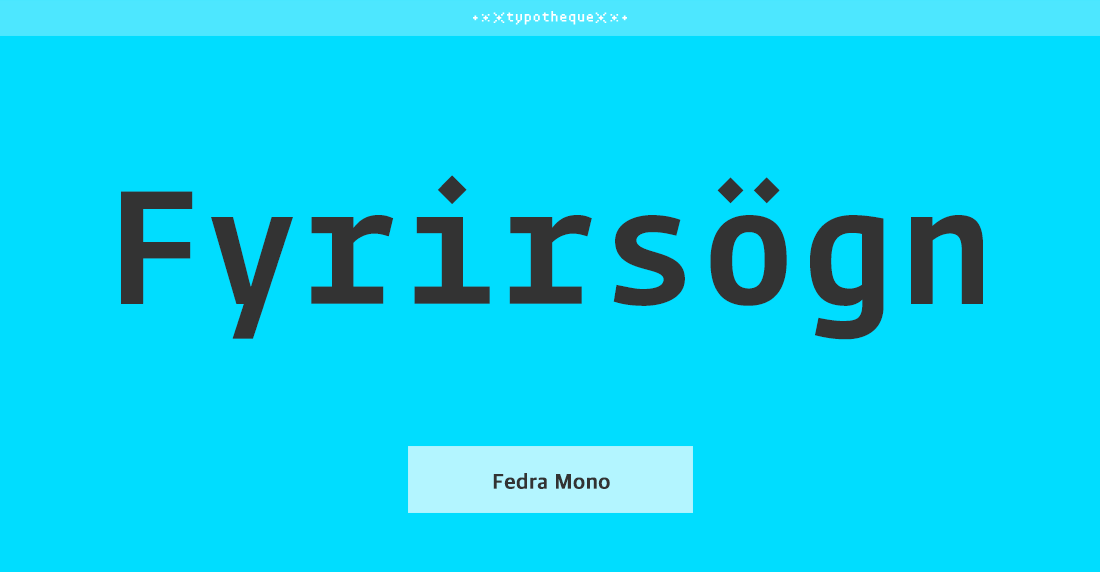
- Fedra Mono Std의 모든 글립은 각각 동일한 폭을 공유하며, 이는 문자의 수직 정렬을 통해 표 형식과 같은 레이아웃에 적합하다.
대표적으로 스프레드 시트, 컴퓨터 코드, 통신문 등에 사용이 가능하다.
폰트 정보 구분 고딕 디자인디렉팅 Peter Biľak 출시년도 2002